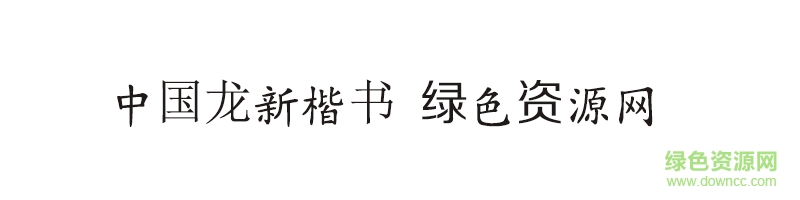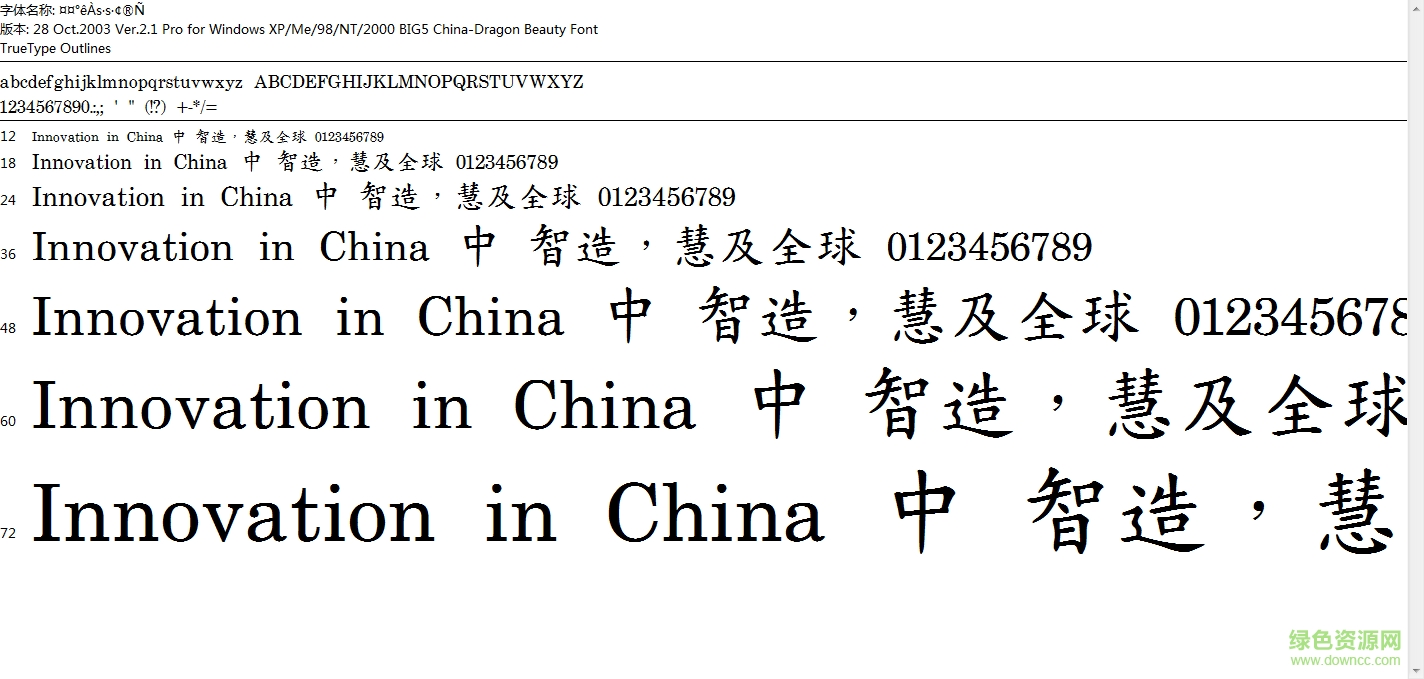
中國龍新楷書是一款非常優(yōu)秀的中文字體,該字體全面支持中英文的輸入轉(zhuǎn)換,字型微妙微翹,絲毫不影響中國龍字體的特色,整體效果非常不錯,喜歡的朋友歡迎來綠色資源網(wǎng)下載!
中國龍新楷書字體保留了楷體字體的原型,整體結(jié)構(gòu)更柔和,簡單易懂,支持中英文顯示,適用于各大windows系統(tǒng)。